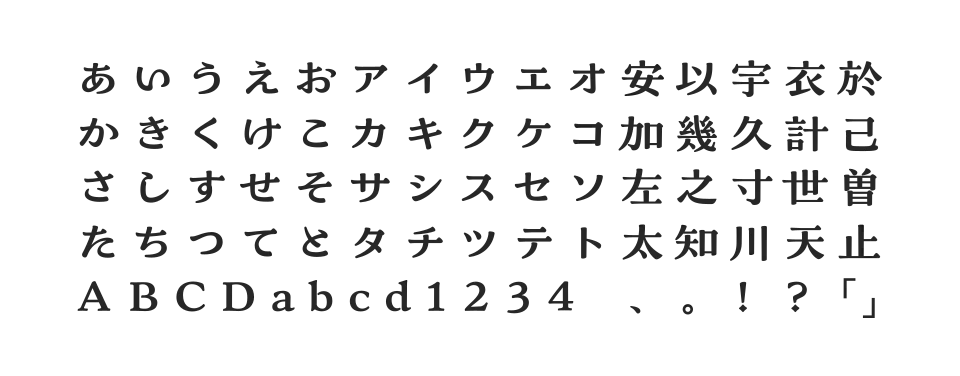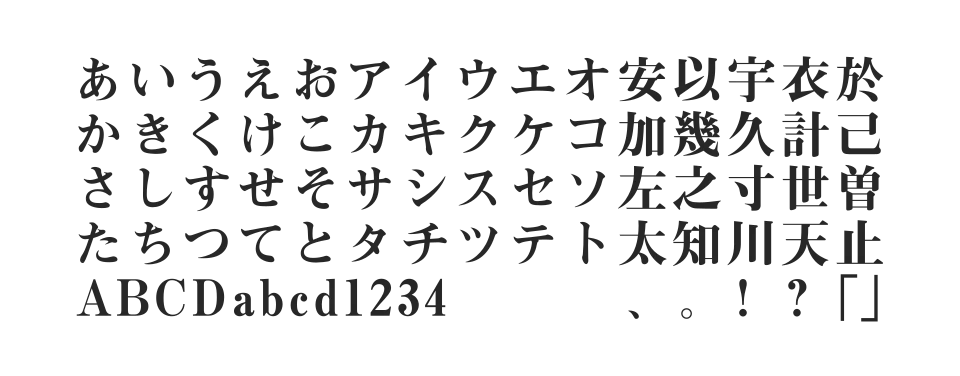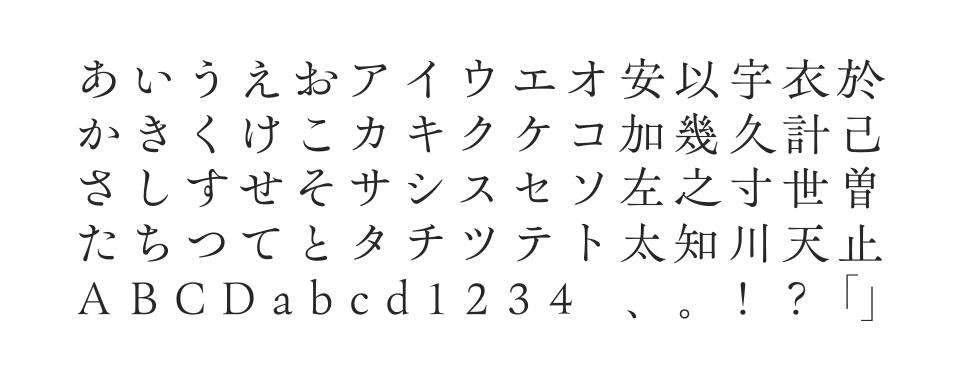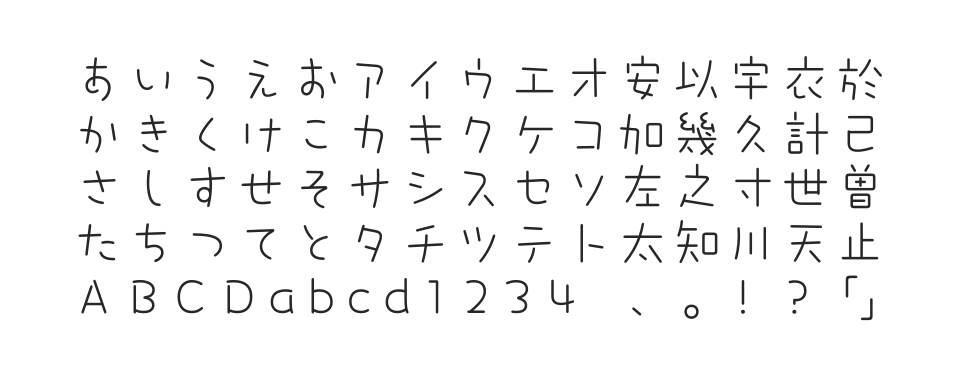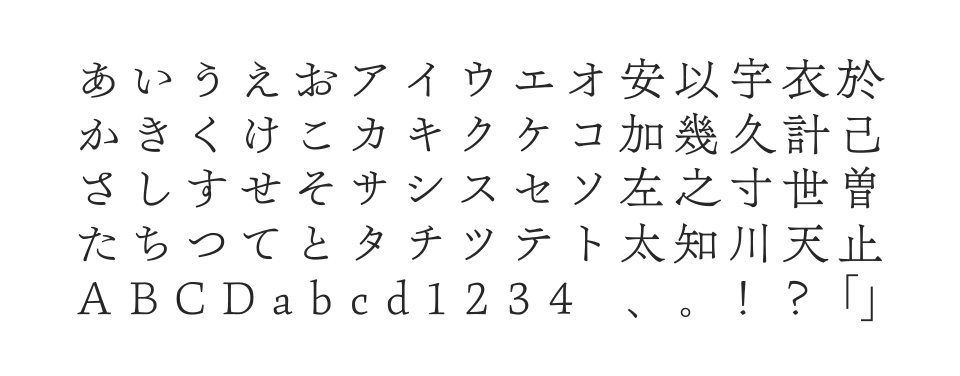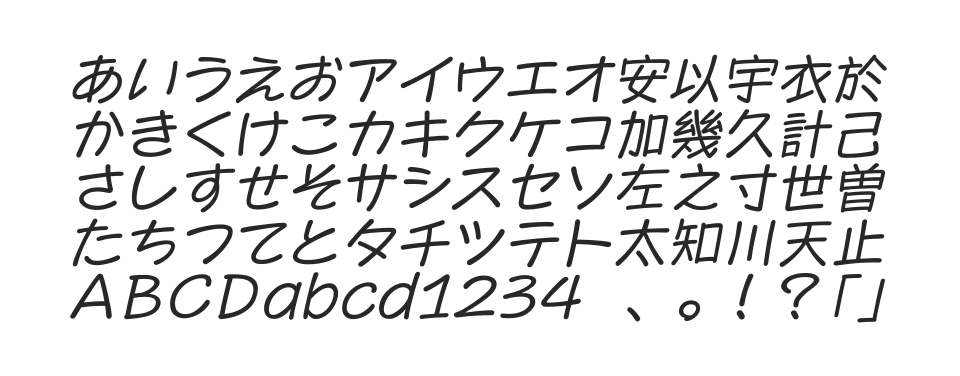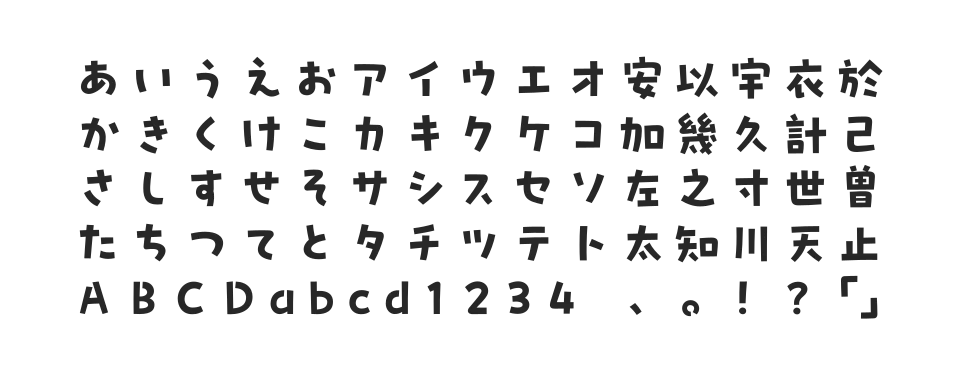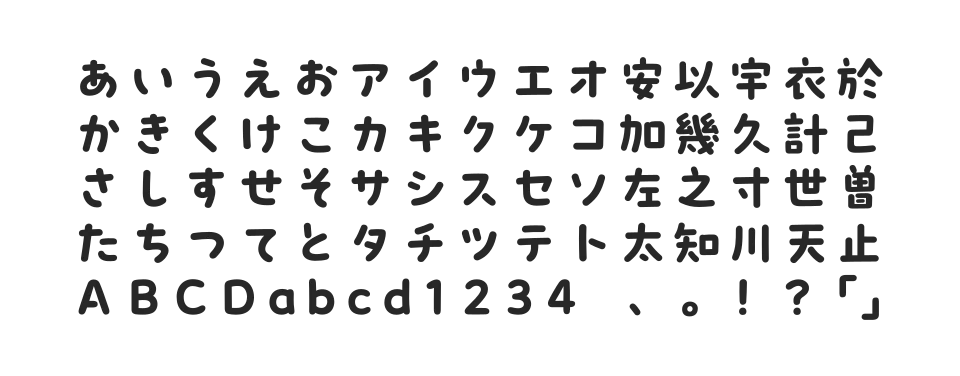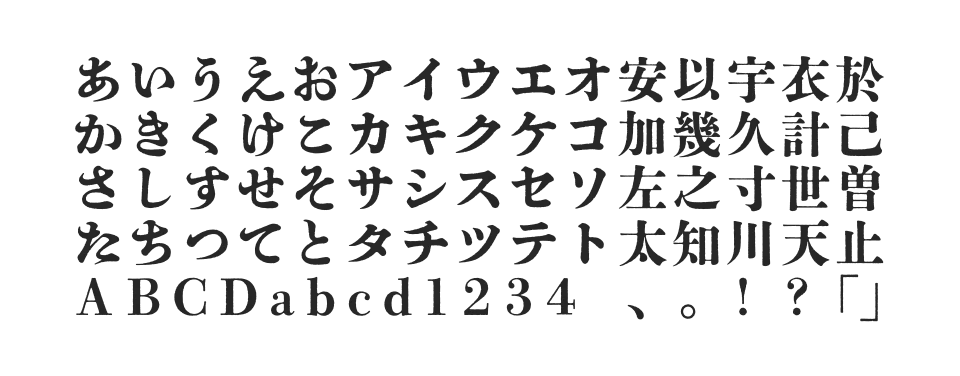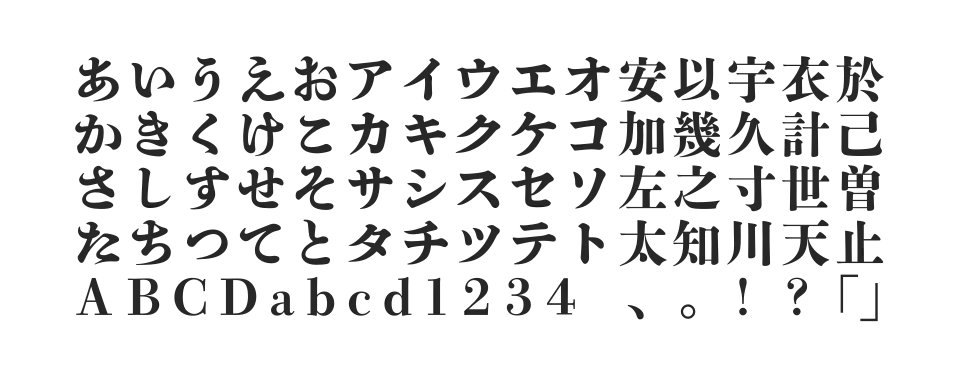
見出しや児童書で使われていた秀英四号明朝太かなを復刻。秀英初号明朝との組み合わせで総合書体化された、筆勢を活かした力強いかな書体です。
秀英体の金属活字を復刻したにじみ系フォント。インクのにじみや温かみのある表現で、やわらかな印象を演出する見出し向けの書体です。
丸ゴシック体風のデザインとやや幾何学的なプロポーションが特徴。もちもちとした線質で、やわらかい印象を持つプフシリーズの2022年新書体です。
ゴシック体風のデザインながら角の折り返しにカーブを取り入れた、力の入りすぎない可愛らしさを表現するプフシリーズの2022年新書体です。
広くデザインしたふところと、ループを強調したかなが特徴の明るい雰囲気を持つ書体。手書きの勢いと傾きによる自然な印象が魅力の2022年の新書体です。
クラシカルな印象を持つ明朝体系のデザイン書体。筆や活字の雰囲気を残したオールドスタイルで、伝統的で格調高い表現が可能な2022年の新書体です。
筆ペンで書いた文字をイメージしたゆる可愛い雰囲気の書体。重心が低くアンバランスな骨格、短く直線的なストロークが、あどけなさや素朴さを演出します。
クラシカルな印象を持つ明朝体系のデザイン書体。筆や活字の雰囲気を残したオールドスタイルで、上品で洗練された表現が可能な2022年の新書体です。
重厚さと風格を備えた伝統的な見出明朝体。確かな太みと存在感をもつ漢字に対して、かなはやや細めに設計されており、モリサワ基本7書体の一つです。
書き文字や金属活字の要素を取り入れた、古風で可愛らしい明朝体風のデザイン書体。平体気味のプロポーションで、レトロな可愛さを演出する2022年の新書体です。